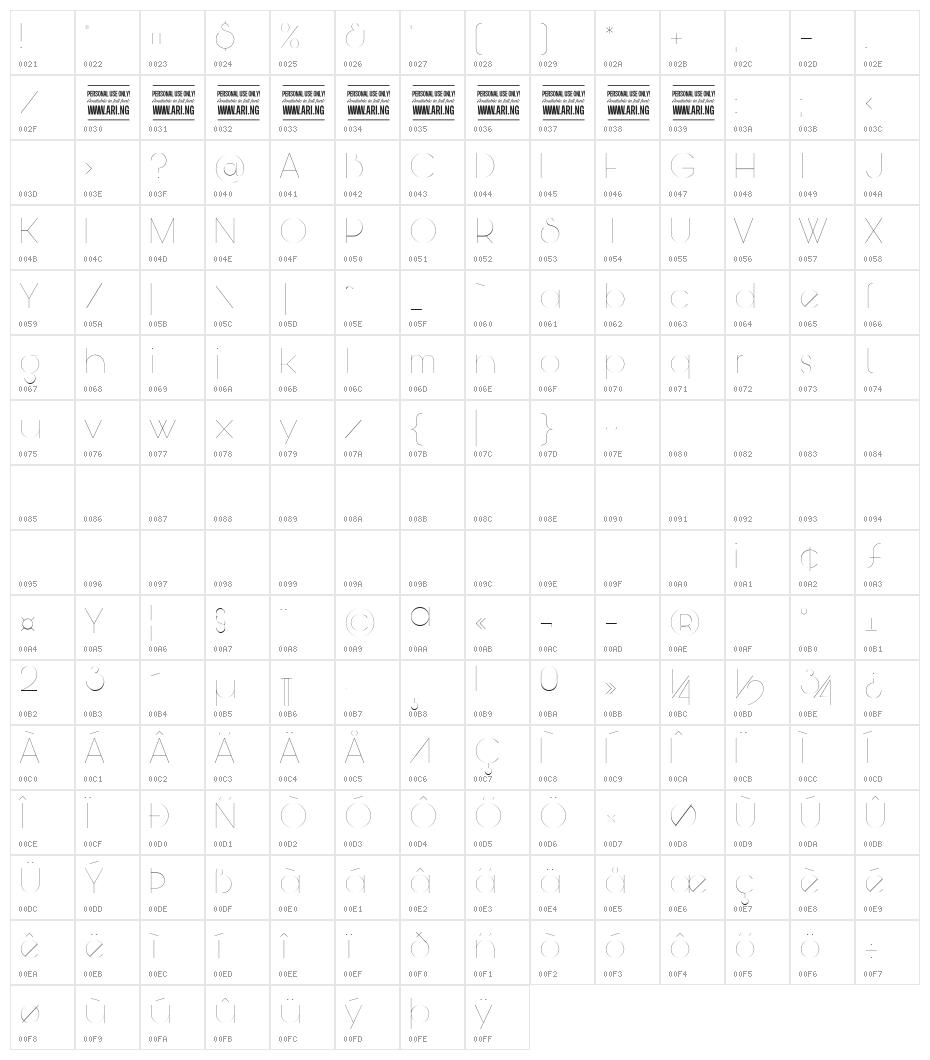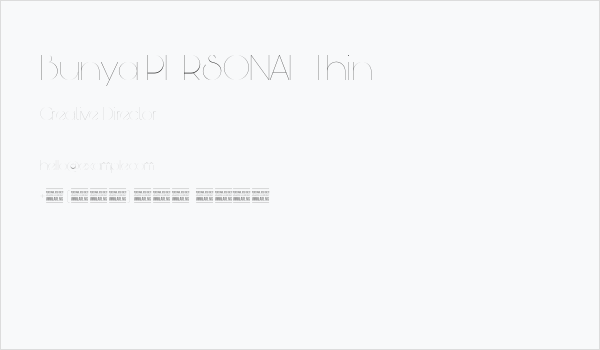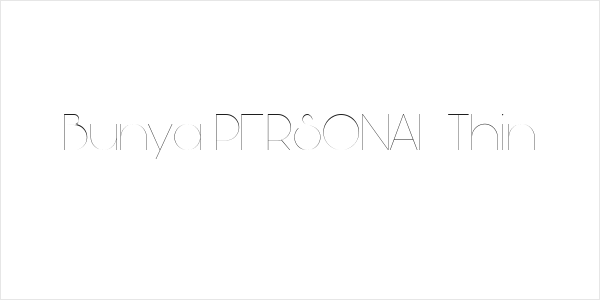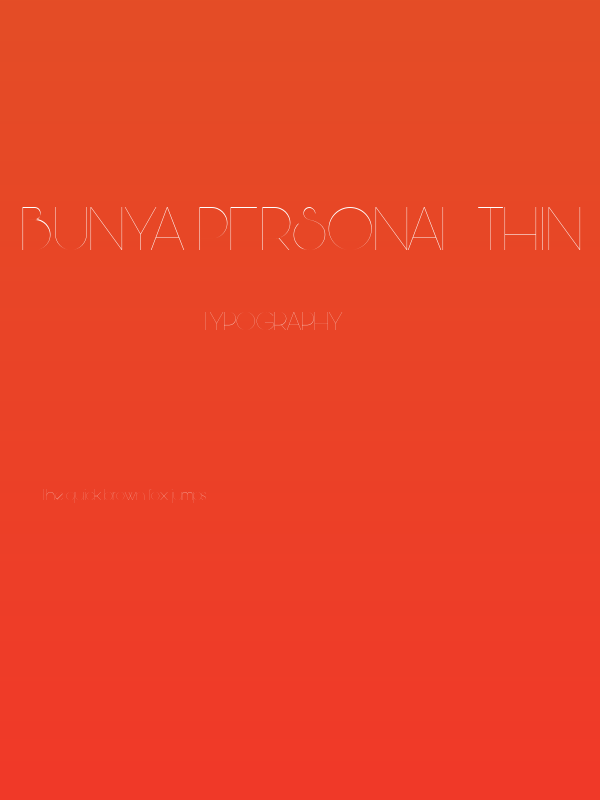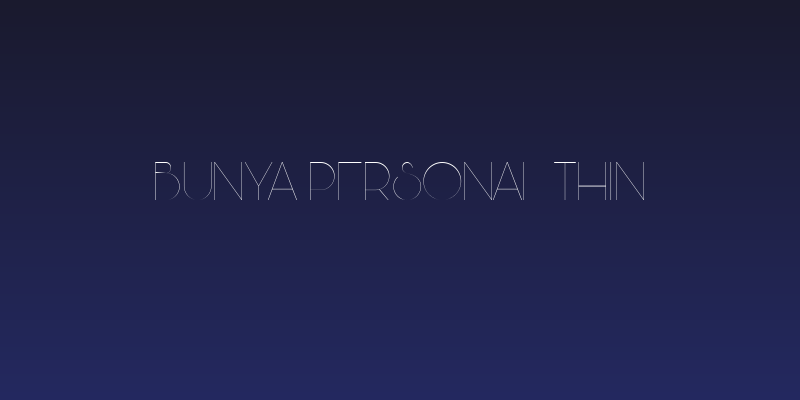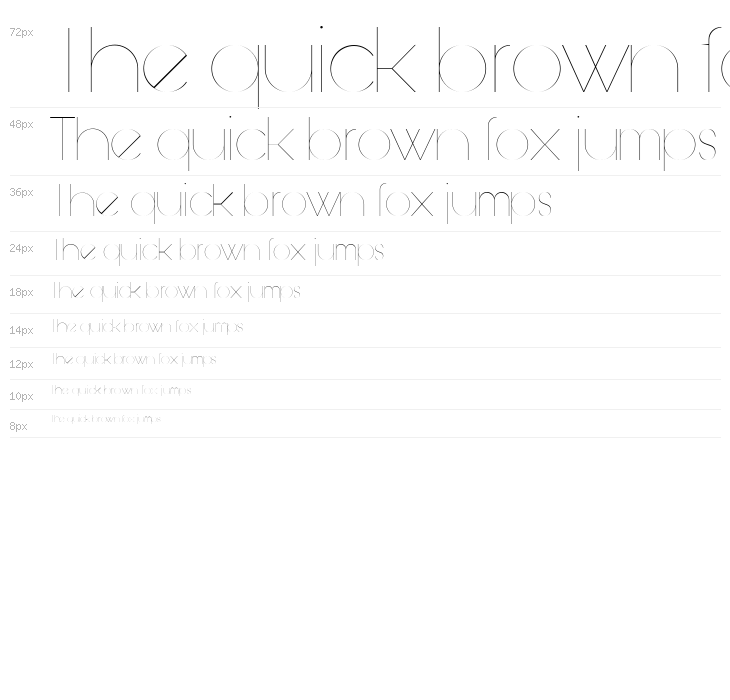
Bunya PERSONAL Thin Font
✎ Sans Serif
| Vorgeschlagene Projekte | Ideal for modern branding, minimalist posters, sleek website headers, and elegant invitations. |